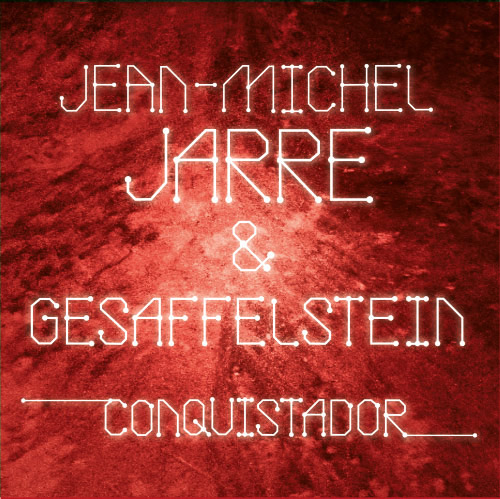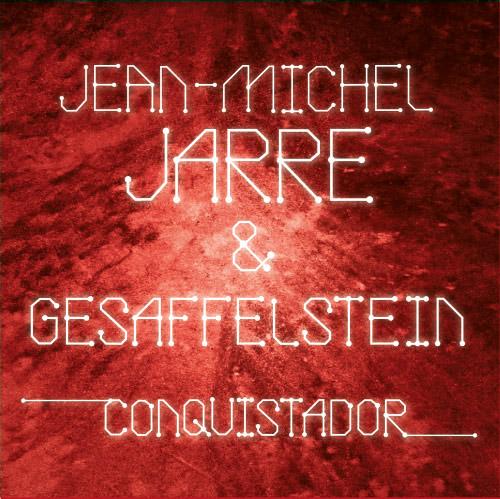
Platinen-Font von Jean-Michel Jarre
ich habe jetzt lange getüftelt und gesucht, aber noch keine weitere Lösung gefunden. Gesucht wird ein Platinen-Font, der zur Zeit sehr massiv in den Videos von Jean-Michel Jarre (zu seinem neuen Album „Electronicaâ€) eingesetzt wird. Ein Bildbeispiel ist angehängt. Natürlich gibt es sehr vielen andere Platinen-Fonts, aber diesen hier habe ich noch nicht ausfindig machen können.
Youtube-Beispiel (am Anfang und Ende kommt’s vor):